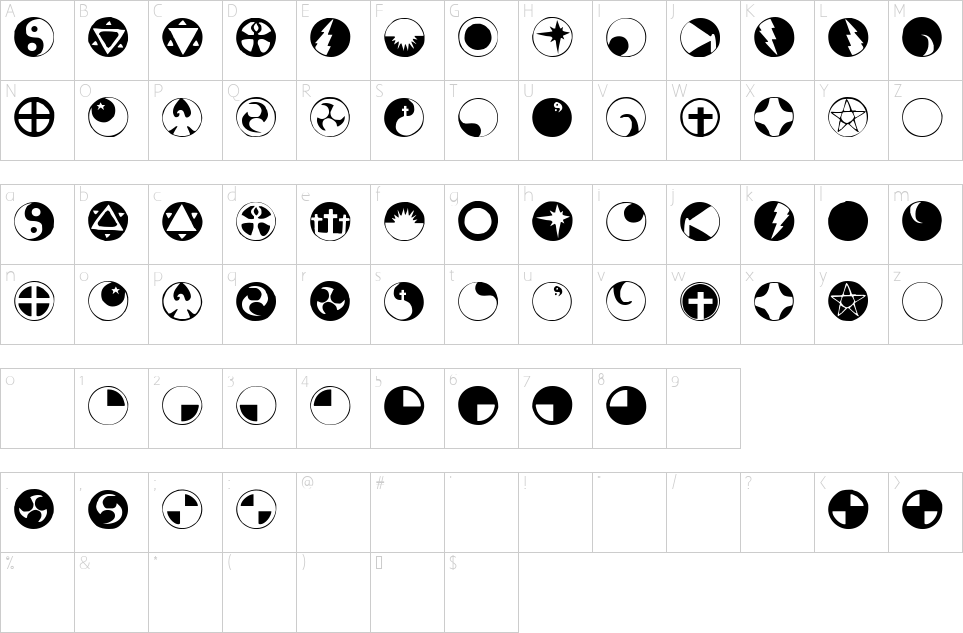
A fonte Obsidiscs é uma opção perfeita para qualquer designer que está em busca de uma fonte moderna e minimalista. Desenvolvida pela Iconian Fonts, esta fonte foi projetada para oferecer um equilíbrio entre elegância e simplicidade. Com 4.064 downloads, a Obsidiscs demonstra o quanto designers e estilistas estão apaixonados por sua beleza e versatilidade. Seja para projetos de design gráfico, criação de logotipos ou até mesmo para adicionar um toque único a mensagens digitais, a fonte Obsidiscs é uma escolha inteligente. Ideal para aqueles buscando uma fonte fresca e atraente para dar um novo jeito aos seus trabalhos. A Obsidiscs é uma ótima fonte gráfica para quem busca um equilíbrio entre elegância e simplicidade.